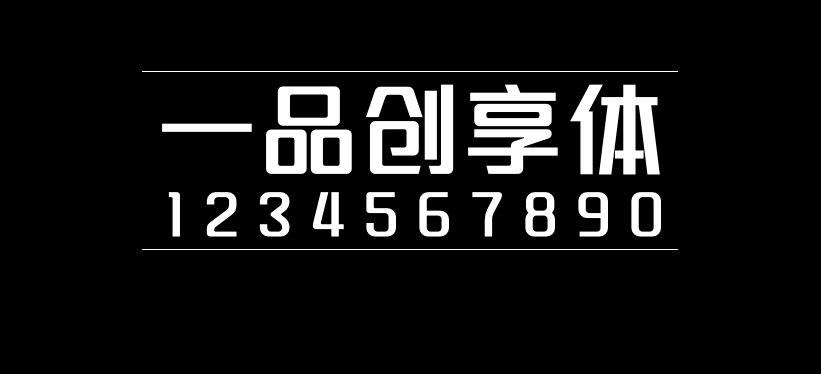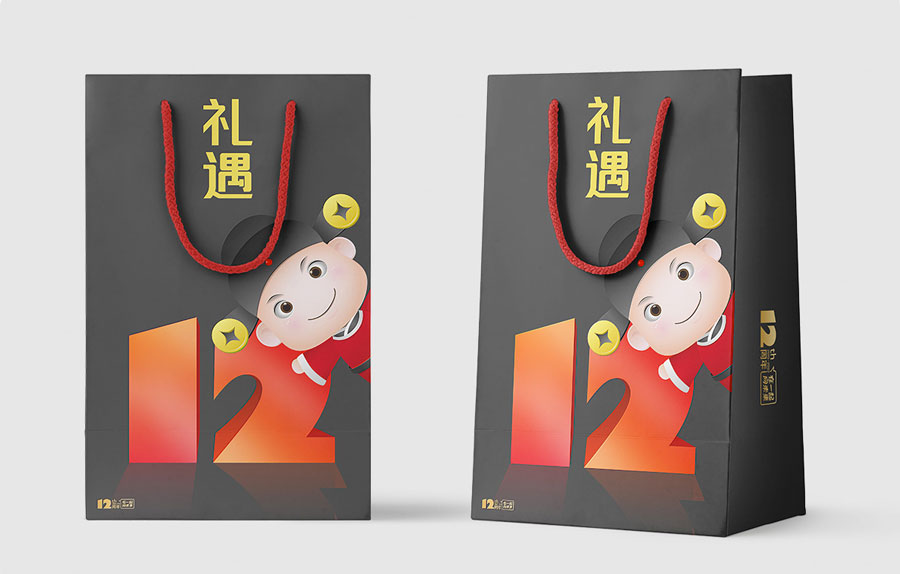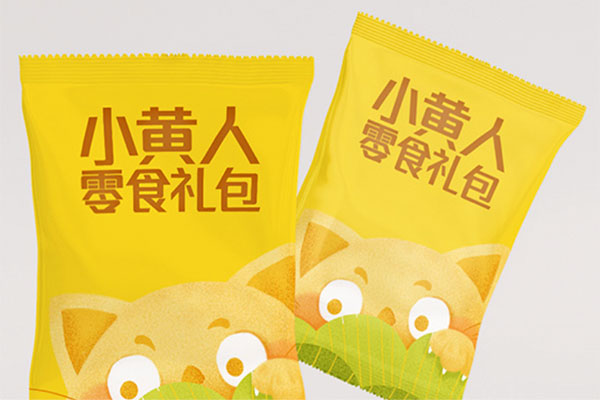
一品创享体
一品创享体是吉页字库创始人孙新恒先生受一品威客邀请作为主创设计师,联合打造的一款公益造字百人计划的字体。
一人设计字库产品要求整体风格统一、字型规范都是一件巨大而艰难的工程,此次活动由N多人参与,更是难上加难。但是,在经过小伙伴们的努力与反复的修改,最终一品创享体还是接近完美的呈现了出来。
造以此字,献礼一品威客网上线运营12周年
一品创享体
版本号1.0,2022年7月最新版。基于中华人民共和国GB2321-80字符集汉字部分标准,共收容汉字3500个,英文及标点等常用字符184个。
作者信息
主创设计师:孙新恒
参与设计师:孔维星、黄秋颖、林小真、田恬、吴升宏、张志彬、郝阳、严卫琳、张玲菱、周鸿珠、于立珺、胡庆胜、李海霞、闭永华、戴富和、黄海光、韦健、韩超
关于一品创享体
一品创享体是威客行业首款公益字体。由全国领先的创意众包服务平台-品威客网发起,采用“主创设计师+多位字体设计师”共同创作的模式,通过一品威客平台众包方式进行创意协助,历时数月共同完成的。这是一套属于全行业创业者的字库创作,字体创作成功后供所有人永久免费下载。“威客”是利用互联网创新创业的一种新模式,我们希望全行业的创业者能永葆创业精神,勇攀发展高峰,通过平台迅速实现创业创收,体现一种自强不息、创享未来的时代精神。字体整体风格具有互联网属性,创意、青春、简约,适合用作标题、促销文案、广告宣传语等使用场景。需要注意的是一品创享体虽然面向社会永久免费使用(含商用),但禁止用于违法用途,禁止再任何场景下改变字体原有名称,禁止将字体以任何形式进行售卖牟利。